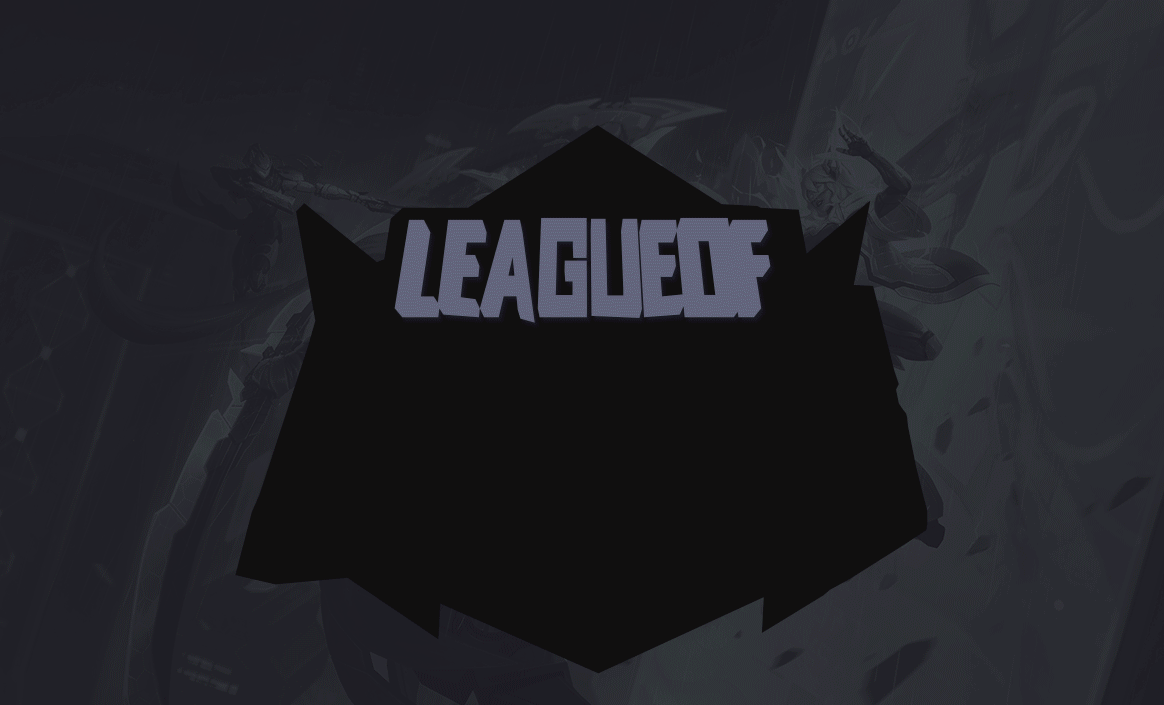
(银河魔装机神)字体设计
在临摹字体设计时,我还将这个设计做成了三维场景,三维场景有更强的渲染效果,给人更好的视觉体验。
下方两张动效图中清晰的展示了字体效果刻画的过程。。。。。。
菱角分明的字形非常适合游戏,加上立体效果和金属材质的加成,视觉效果很不错。
科技感十足的字形也有不错的视觉效果
动效图
字体设计静态展示